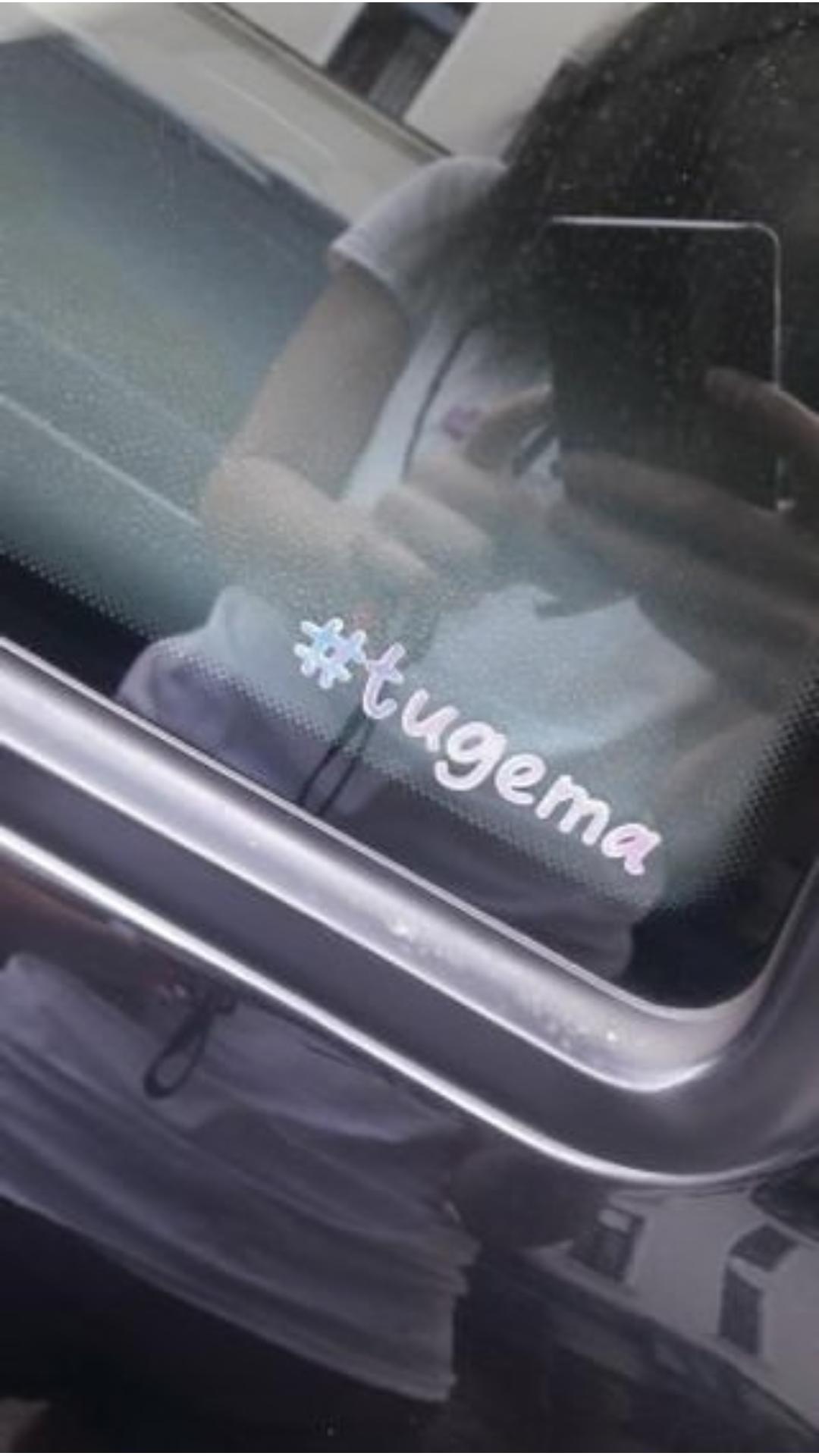
suche diese Schriftart vom Bild #tugema
Ich würde ja fast sagen, dass die Schrift eine Handschrift ist. Sieht so fingerfarbig geschrieben aus.
nee, ich weiß nur das es eine kostenlose Font von dafont.com sein soll.
Leider weiß ich aber nicht mehr welche 😞 Der Inhber leider auch nicht mehr, da der Drucker es wohl nicht mehr einsehen kann. Er hat wohl nur eine Bild Datei gespeichert für die Aufkleber 😕
Und mit diesem Wissen sollte der Font auch zu finden sein. Muss man sich einfach durch die entsprechenden Schreibschriftkategorien wühlen.
Wie Ralf schrieb, einfach wühlen!
https://www.dafont.com/de/nocturnal-hand.font?fpp=100&text=%23tugema
Kategorie Schreibschrift/Handgschrieben, ohne weitere Filter, auf Seite 4 (bei 100 Schriften pro Seite mit #tugema als Vorschau). 🙂